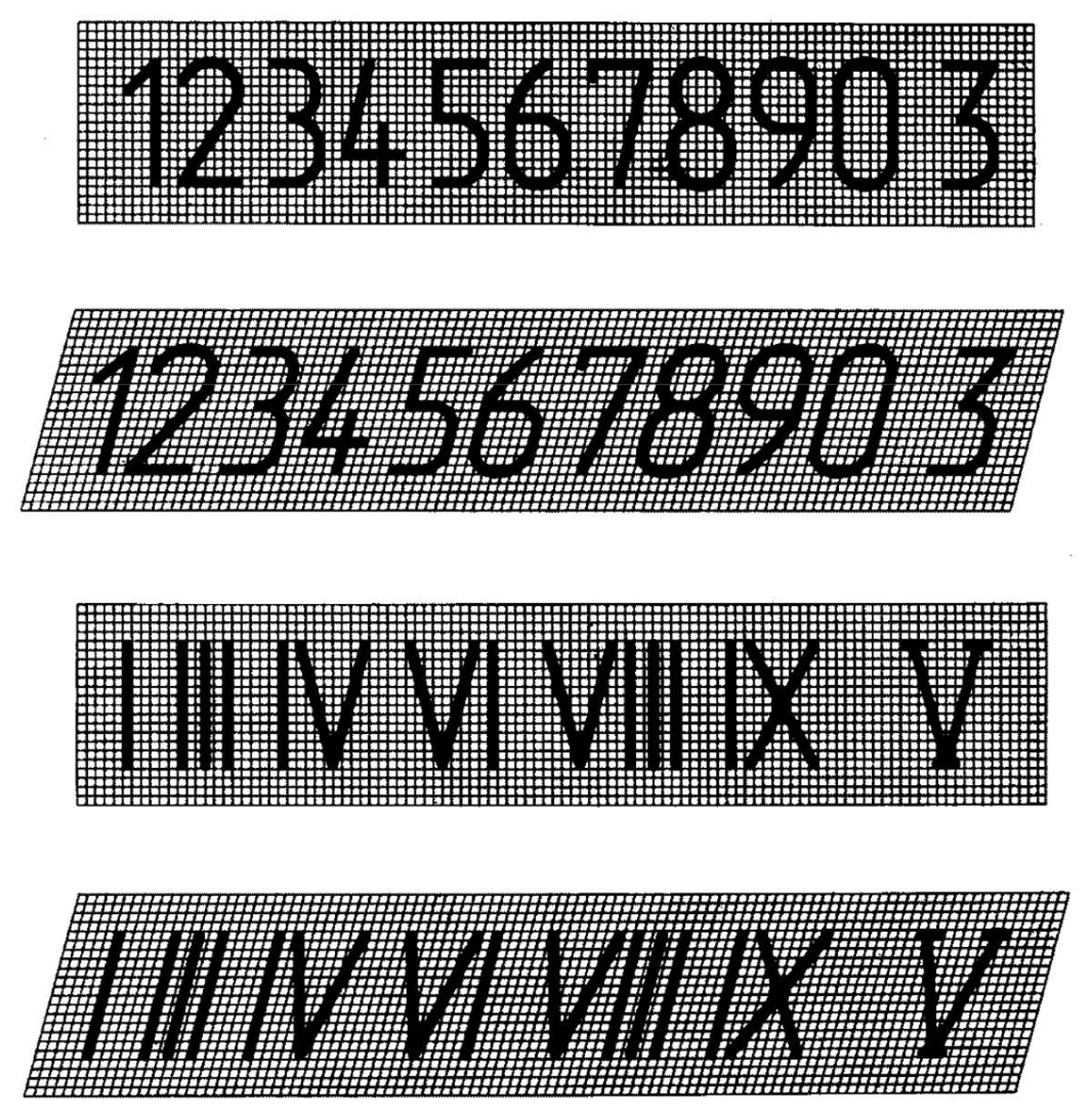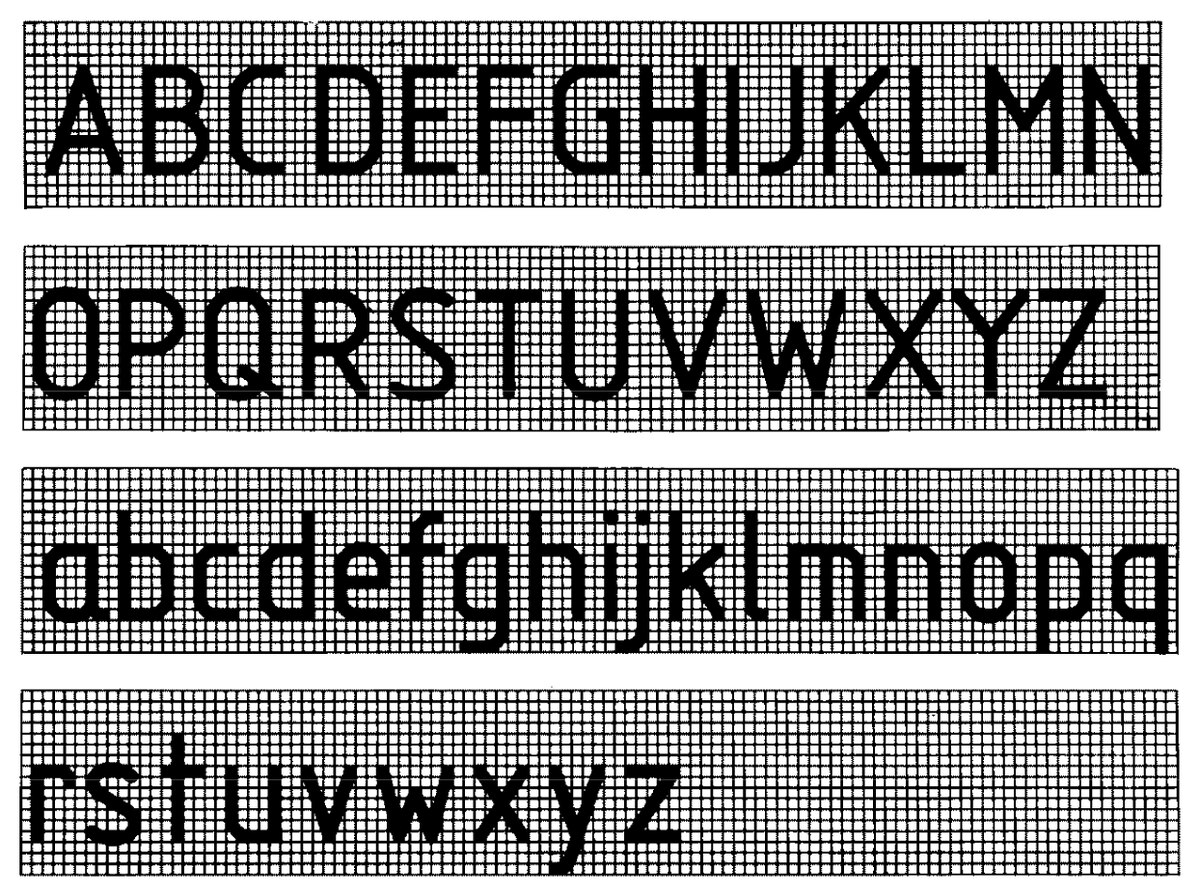
Прописи. Учимся писать печатные буквы И.
Когда-то первоклашки в обязательном порядке проходили этап письма перьевой ручкой. Прошел этот этап и автор. Синие пальцы, неизбежные кляксы в тетрадках, вечно подтекающие дешевые ручки – и неизменно теряющиеся дорогие… Но, несмотря на «приятные» воспоминания, автор отдает предпочтение использованию на первом этапе обучения именно перьевой ручки.